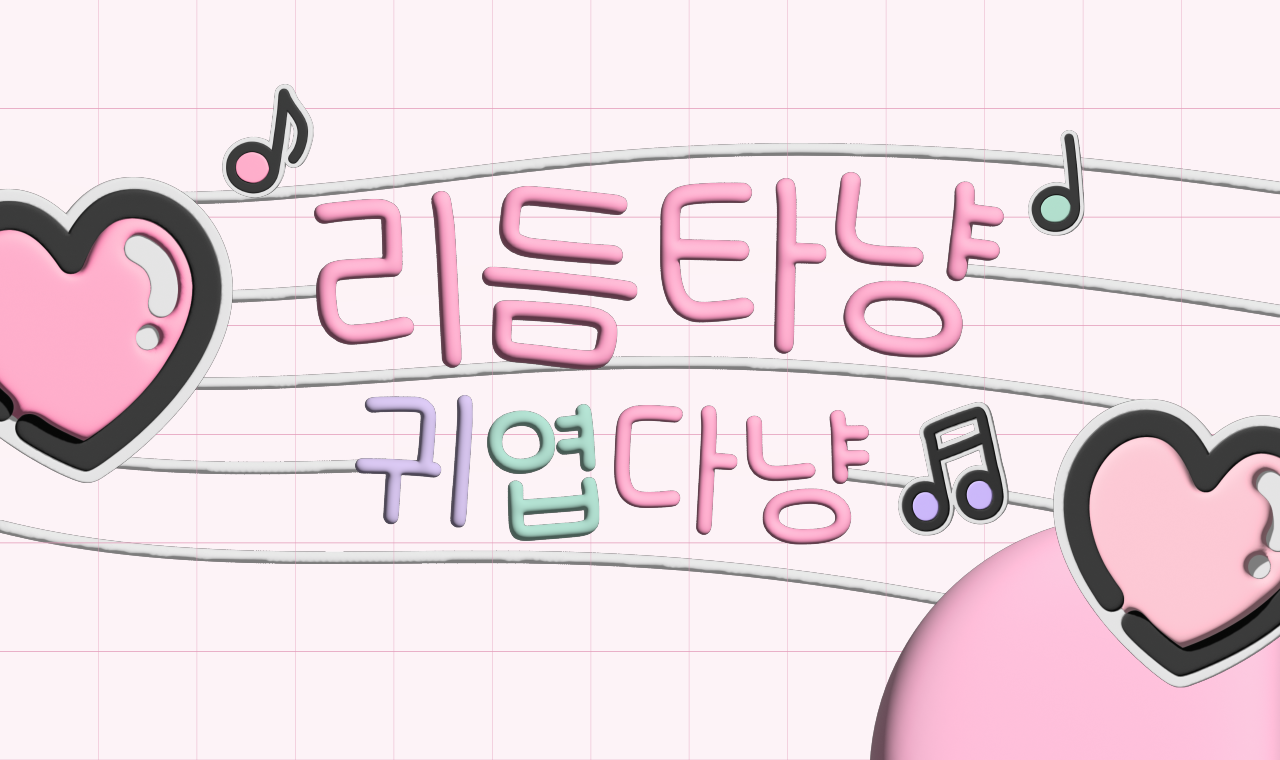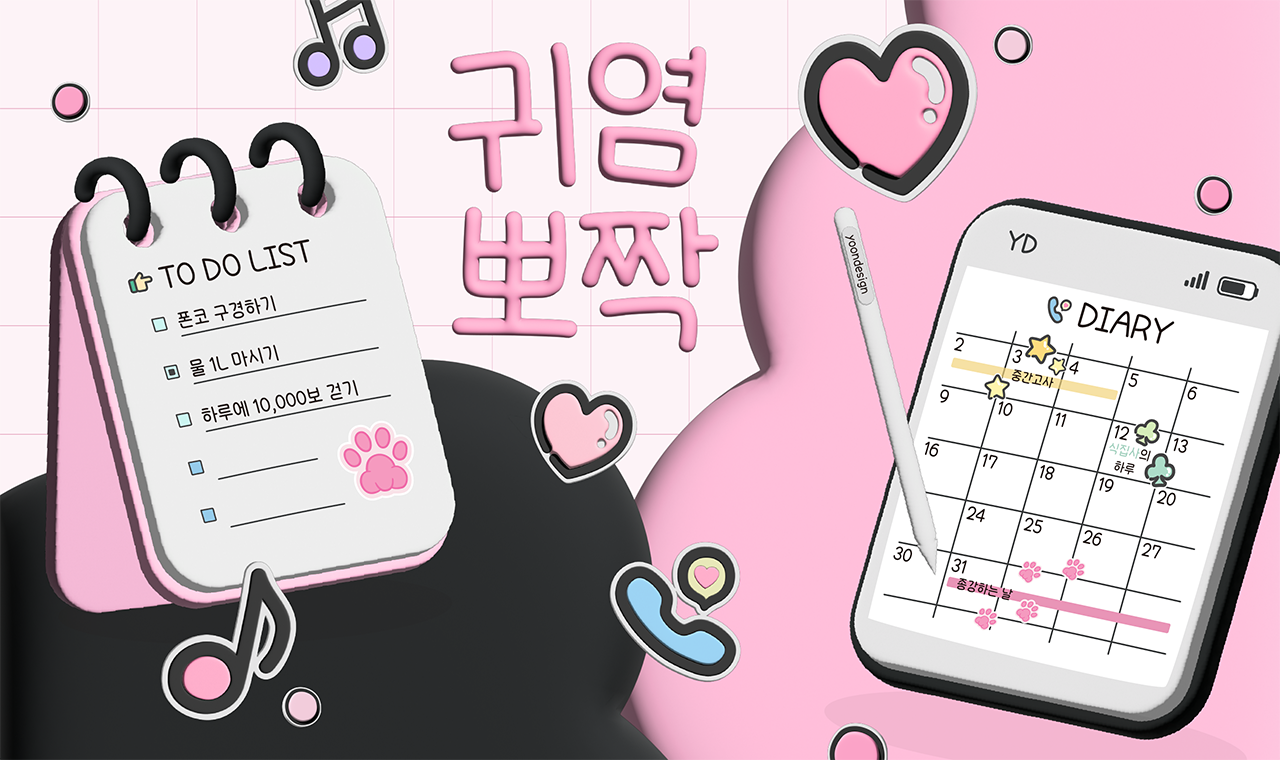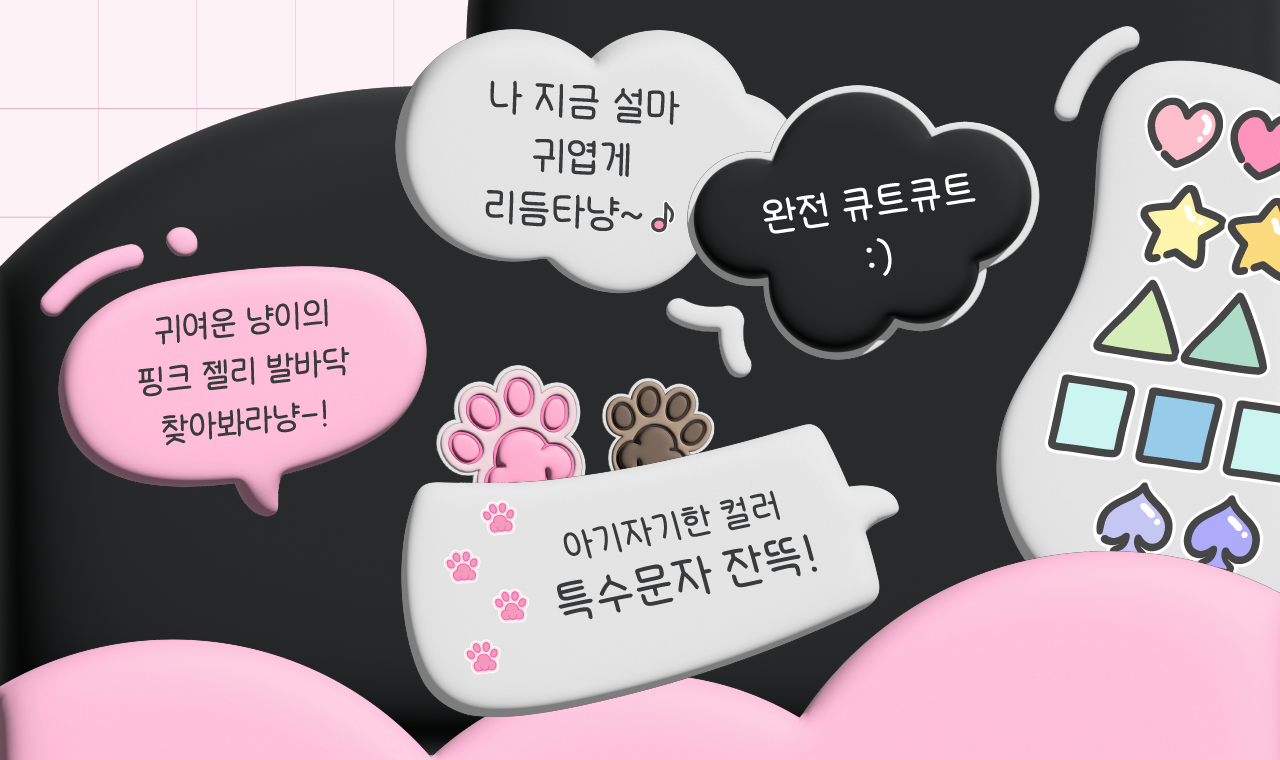
리듬타냥
Yoon 리듬타냥
리듬타냥은 고양이의 유연하고도 귀여운 모습을 떠올리며 제작된 손글씨 서체입니다. 글자의 곡선미와 더불어 큼지막한 한글 자소들은 보는 이에게 귀여운 인상을 더해주며, 도형 특문을 컬러로 제작하고, 고양이의 젤리같은 발바닥을 히든딩벳으로 담아 사용자들에게 재미요소를 더했습니다.